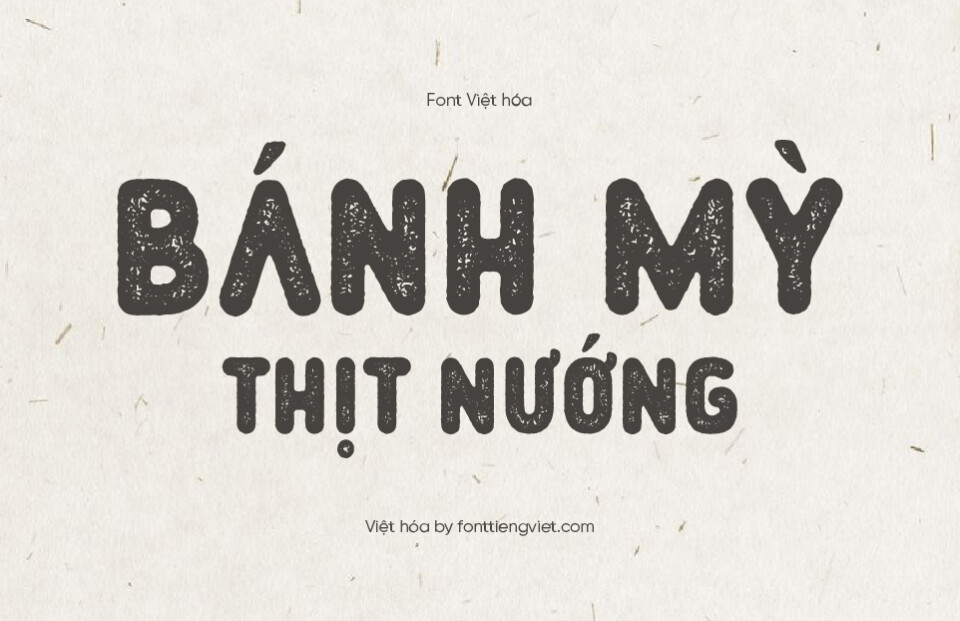
Giới thiệu về Font Việt hóa 1FTV VIP Plopin Rough
Trong thế giới thiết kế đồ họa hiện đại, việc lựa chọn một bộ Font Chữ phù hợp đóng vai trò quyết định đến tính thẩm mỹ của sản phẩm. Font Việt hóa 1FTV VIP Plopin Rough là một lựa chọn hoàn hảo cho những ai đang tìm kiếm phong cách cổ điển, thô mộc nhưng vẫn giữ được nét tinh tế. Đây là phiên bản được tối ưu hóa hoàn toàn cho tiếng Việt, giúp người dùng không còn lo lắng về lỗi hiển thị dấu khi thiết kế các ấn phẩm truyền thông hay tài liệu học tập.
Đặc điểm nổi bật của bộ font chữ ấn tượng này
Phong cách thiết kế độc đáo
Font Việt hóa 1FTV VIP Plopin Rough mang trong mình nét vẽ tay mộc mạc với các hiệu ứng hạt nhám đặc trưng. Kiểu dáng này tạo cảm giác gần gũi, chân thực, cực kỳ phù hợp cho các tiêu đề sách, thiệp mời hoặc các poster quảng cáo mang hơi hướng hoài cổ. Sự kết hợp giữa đường nét dày dặn và bề mặt kết cấu giúp font chữ này nổi bật trên mọi nền tảng thiết kế khác nhau.
Tính ứng dụng cao trong giáo dục và sáng tạo
Đối với học sinh và giáo viên, bộ font này là công cụ tuyệt vời để trang trí bài giảng hoặc làm báo tường. Khả năng đọc tốt cùng bộ ký tự đầy đủ giúp việc truyền tải thông tin trở nên thú vị hơn. Bạn có thể dễ dàng sử dụng trong các phần mềm phổ biến như Photoshop, Canva hay Word để tạo ra những sản phẩm độc bản mang đậm dấu ấn cá nhân.
Kết luận về Font Việt hóa 1FTV VIP Plopin Rough